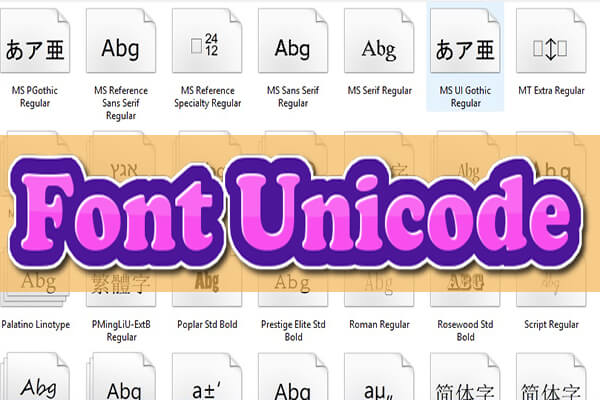
Trọn bộ Font Unicode Free
Font Unicode là một loại phông chữ thuộc bộ font việt hóa đặc biệt được thiết kế để hỗ trợ hiển thị các ký tự từ nhiều ngôn ngữ và hệ thống viết trên toàn thế giới. Bộ Font Unicode là một tiêu chuẩn mã hóa ký tự quốc tế, cho phép các ký tự từ các bảng chữ cái khác nhau, bao gồm cả tiếng Việt, tiếng Trung, tiếng Nhật, Ả Rập và nhiều ngôn ngữ khác, được hiển thị đúng cách trên bất kỳ nền tảng nào. Các Font Unicode như Arial, Times New Roman thường được sử dụng rộng rãi vì khả năng hỗ trợ đa ngôn ngữ của chúng. Với tính đa dạng và khả năng tương thích cao, bộ Font Unicode là lựa chọn hàng đầu cho các tài liệu, trang web và phần mềm cần hiển thị chính xác nội dung đa ngôn ngữ.